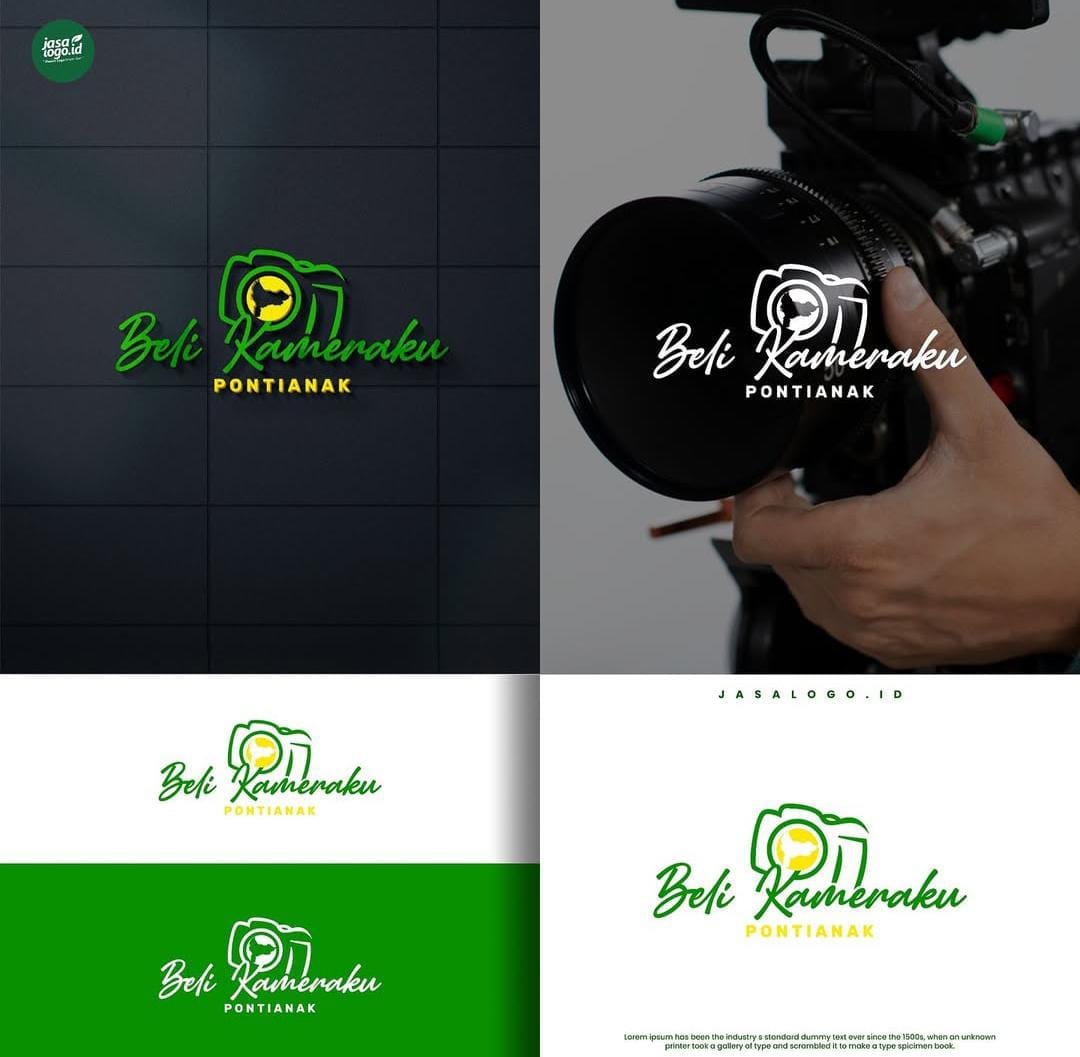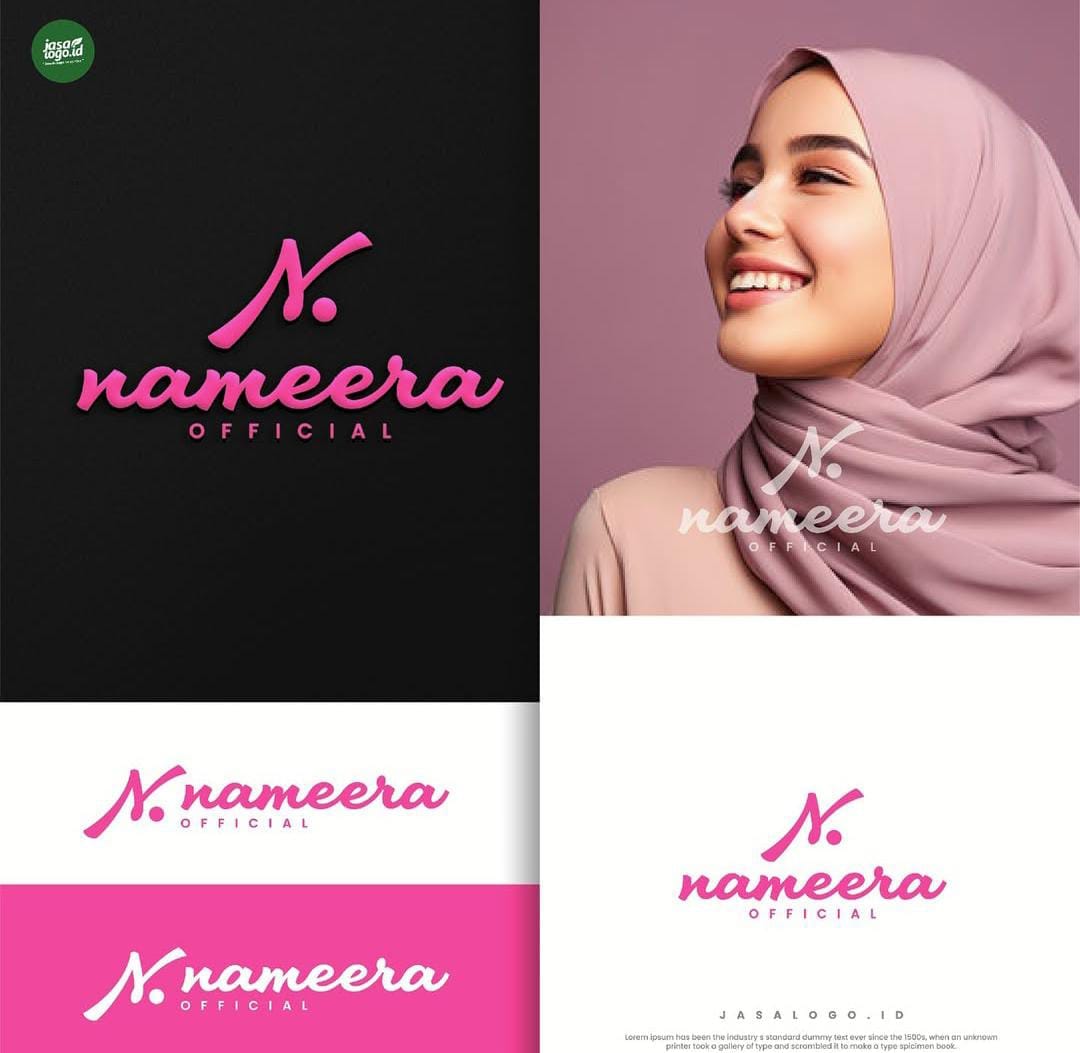
Perbedaan Style Font Script Tipis dan Tebal dalam Logo
Gaya tipografi dalam desain logo berperan memudahkan keterbacaan nama brand serta menciptakan visual logo yang menarik. Style font script yang bergaya seperti tulisan tangan akan menciptakan kesan yang lebih personal dan unik. Dalam desain logo penggunaan font script dapat memilih style font tipis dan tebal sesuai dengan kebutuhan.
Style font script memiliki banyak variasi gaya huruf mulai dari tipis, reguler, tebal hingga tajam dan bulat. Setiap gaya huruf bisa merepresentasikan kesan yang berbeda sehingga perlu dipilih sesuai karakter brand. Gaya font script dalam desain logo perlu juga dipilih yang unik dan yang mudah untuk dibaca.
MAKNA PSIKOLOGI FONT SCRIPT
Dalam membangun identitas brand yang kuat, penting untuk memilih font dengan mempertimbangkan makna psikologisnya. Setiap bisa merepresentasikan karakter atau kesan tertentu, baik gaya huruf yang tipis maupun yang tebal. Style font script dalam desain logo bisa memiliki beberapa makna psikologi seperti:
• Fancy: Font script yang tipis dan tajam, bisa menciptakan kesan brand yang mewah. Biasanya cocok untuk brand seperti kecantikan dan fashion
• Kreatif: Gaya huruf script juga bisa menciptakan kesan kreatif dan ramah, terutama jika memiliki huruf tebal dan bulat.
• Aneh atau Misterius: Font script yang tipis juga bisa menciptakan kesan misterius. Biasanya yang memiliki garis tulus tidak terlalu halus dan bertekstur.
• Feminim: Style font yang elegan juga dapat digunakan untuk menciptakan brand yang feminim dan elegan.
Penggunaan font yang bergaya seperti tulisan tangan pada desain logo akan menciptakan berbagai kesan. Hal ini bergantung pada gaya huruf yang digunakan, ada bisa tampil elegan, personal dan feminim. Berikut perbedaan style font script dalam beberapa desain logo brand, yaitu:
Font Script Tipis Elegan Logo Beli Kameraku
Gaya huruf script yang tipis akan menciptakan visual yang elegan, sehingga sering dipilih mencerminkan brand elegan dan mewah. Font script yang tipis pada logo tersebut memiliki tampilan elegan karena garis halus dan tajam. Tipografi script pada logo juga tidak terlalu tipis sehingga memiliki keterbacaan yang baik.
Garis huruf yang tampak elegan efektif merepresentasikan identitas brand yang elegan. Gaya font script tipis yang elegan tersebut memiliki style huruf miring sehingga tampil semakin elegan.
Font Script Tipis Tulisan Tangan
Penggunaan font script yang tipis ada yang tampil lebih ramah seperti tulisan tangan. Jika ada font script yang tajam dan tipis, font pada logo tersebut berkesan lebih personal. Penggunaan font tipis bergaya tulisan tangan tersebut bisa menciptakan pula kesan brand kreatif dan premium.
Desain logo wine tampil minimalis dan bersih, sehingga penggunaan font tipis seperti tulisan tangan tampak harmonis. Gaya huruf script tipis pada logo juga mudah dibaca karena jarak huruf yang tidak begitu rapat. Ketebalan huruf sama dengan style line art ikon logo sehingga menciptakan visual yang harmonis.
Font Script Tajam dan Tebal
Sementara itu style font script yang tebal akan membuat tipografi mudah dibaca dan lebih menonjol. Gaya huruf tulisan tangan yang tebal harus dipilih ketebalan yang pas agar tidak membuat teks sulit dibaca karena terlalu rapat. Gaya font script tebal pada logo tersebut menggunakan gaya huruf yang tebal dan tajam.
Kombinasi gaya huruf script yang tebal dan tajam tersebut juga menciptakan kesan elegan. Font tersebut memiliki huruf miring yang tajam dan tebal sehingga cocok untuk merepresentasikan brand fashion. Penggunaan tipografi tebal membuat nama brand mudah dibaca dan menciptakan kesan yang menonjol.
Font Script Tebal dan Bulat
Biasanya gaya huruf script latin akan memiliki gaya huruf tebal tetapi garis penghubung yang tipis sehingga menyisakan ruang negatif. Jika terlalu tebal dan rapat, keterbacaan font latin akan semakin sulit. Desain logo salon kecantikan tersebut menggunakan font script agar berkesan elegan dan feminim, tetapi juga menonjol.
Gaya huruf yang bulat pada logo salon tersebut membuat nama bisnis mudah terbaca dan tampil menonjol. Selain itu gaya huruf script yang tebal dan bulat tersebut menciptakan kesan yang ramah dan elegan. Sudut-sudut yang tidak begitu tajam dalam logo tersebut membuat logo tampil lebih ramah dan mudah terbaca.
Font Script untuk Kontras
Dalam desain logo, gaya font script digunakan membuat desain logo tampil menarik dan elegan. Gaya huruf yang unik dan bisa kontras jika dikombinasikan dengan font sederhana. Pada logo tersebut font script yang digunakan memiliki gaya huruf tipis dan digunakan sebagai font sub judul.
Style font script dalam desain logo dapat memiliki banyak gaya huruf dari yang tipis, tebal, bulat dan tajam. Penggunaan gaya huruf script bisa mencerminkan kesan brand elegan, feminim dan kreatif. Pastikan memilih gaya huruf yang tepat agar font script mudah dibaca dan mencerminkan karakter brand yang sesuai.